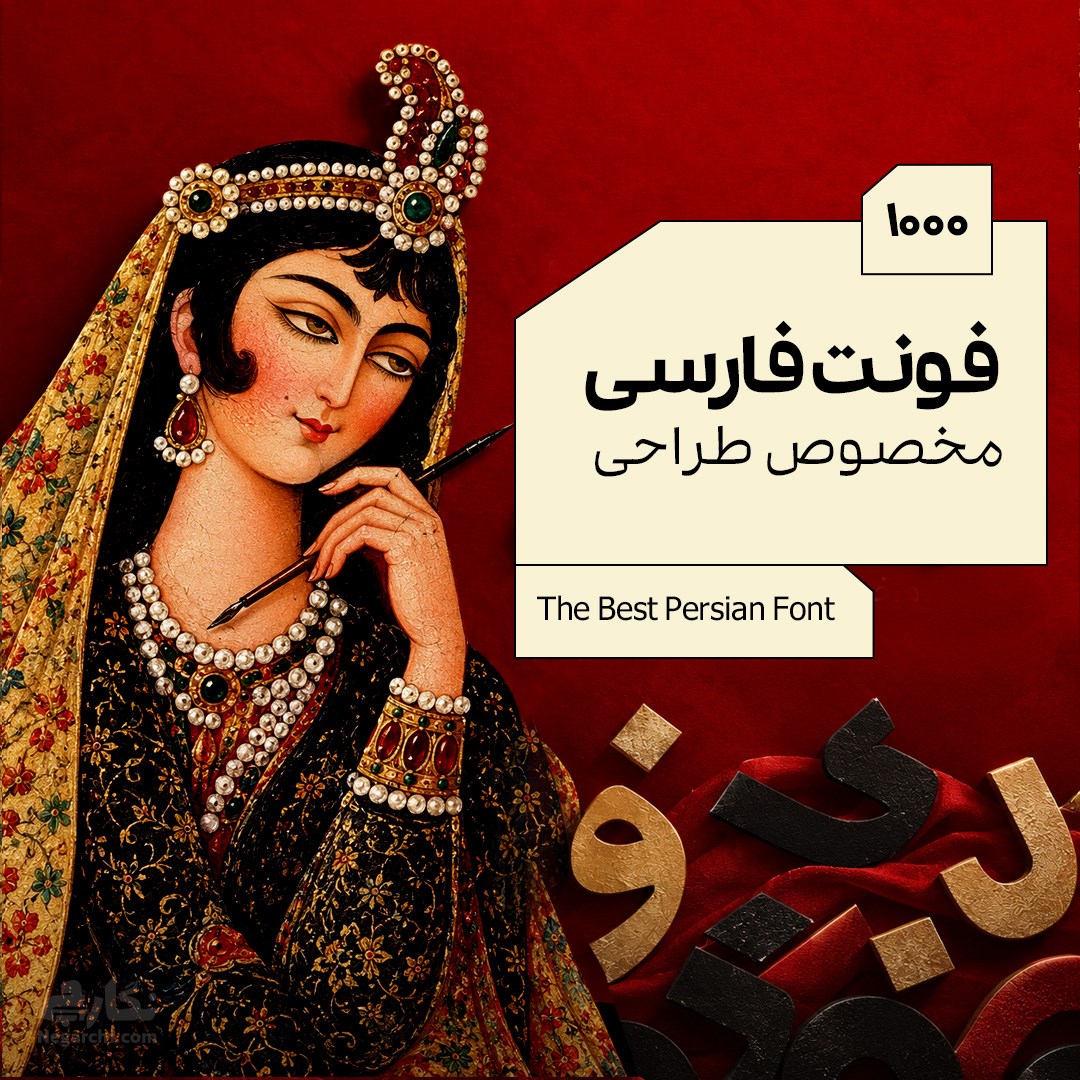
مجموعه 1000 فونت فارسی مخصوص طراحی، دستهبندیشده و مرتب، شامل فونتهای باکیفیت در سبکهای وزندار، شکسته، دستنویس و سمبل، مناسب استفاده در سیستم و موبایل.
مجموعه 1000 فونت فارسی مخصوص طراحی یک مجموعه دستهبندیشده و کاملا مرتب از فونتهای متنوع فارسی است که برای استفاده در پروژههای طراحی و تولید محتوای متنی آماده شده است. این مجموعه شامل فونتهای باکیفیت در سبکهای مختلف است تا برای ایجاد ظاهرهای متفاوت در طراحی، انتخابهای بیشتری در اختیار داشته باشید.
فونتهای این مجموعه در چند سبک کاربردی قرار گرفتهاند و انتخاب فونت مناسب را برای پروژههای مختلف سادهتر میکنند. در 1000 فونت فارسی میتوانید فونتهای وزندار، شکسته، دستنویس و سمبل را پیدا کنید و متناسب با سبک طراحی خود از آنها استفاده کنید.
مجموعه 1000 فونت فارسی مخصوص طراحی برای استفاده در سیستم و موبایل در نظر گرفته شده است. وجود سبکهای متنوع باعث میشود بتوانید برای طراحیهای مختلف، از فونت مناسب با ظاهر و کاربرد موردنظر خود استفاده کنید.
1000 فونت فارسی مجموعهای متنوع از فونتها را در چند سبک کاربردی در اختیار شما قرار میدهد. در این مجموعه فونتهای باکیفیت، وزندار، شکسته، دستنویس و سمبل قرار گرفتهاند تا برای طراحیهای مختلف گزینههای متنوعی داشته باشید. دستهبندی و مرتب بودن فونتها نیز باعث میشود پیدا کردن سبک موردنظر سادهتر باشد. اگر در پروژههای گرافیکی، تولید محتوای فارسی یا طراحی متنی به انتخابهای بیشتری نیاز دارید، وجود این سبکهای مختلف میتواند روند انتخاب فونت مناسب را سریعتر و کاربردیتر کند.
بله، 1000 فونت فارسی مخصوص طراحی برای افرادی تهیه شده است که در پروژههای مختلف به فونتهای فارسی متنوع نیاز دارند. وجود فونتهای وزندار، شکسته، دستنویس و سمبل امکان انتخاب سبکهای متفاوت را برای طراحی فراهم میکند. این مجموعه میتواند برای طراحان گرافیک، تولیدکنندگان محتوای فارسی و افرادی که برای پروژههای شخصی یا کاری خود به فونتهای متنوع نیاز دارند، کاربردی باشد. انتخاب فونت مناسب همچنان باید بر اساس نوع طراحی، خوانایی و سبک بصری پروژه انجام شود.
1000 فونت فارسی میتواند در پروژههایی که به انتخاب فونت فارسی متنوع نیاز دارند مورد استفاده قرار گیرد. فونتهای وزندار برای ایجاد تأکید و ساخت تیترهای متفاوت، فونتهای شکسته و دستنویس برای طراحیهایی با ظاهر متفاوت و فونتهای سمبل برای کاربردهای گرافیکی میتوانند گزینههای مناسبی باشند. این مجموعه برای طراحان، تولیدکنندگان محتوا و کاربرانی که میخواهند در پروژههای فارسی خود به جای استفاده مداوم از چند فونت محدود، مجموعهای متنوع در اختیار داشته باشند، کاربردی است.